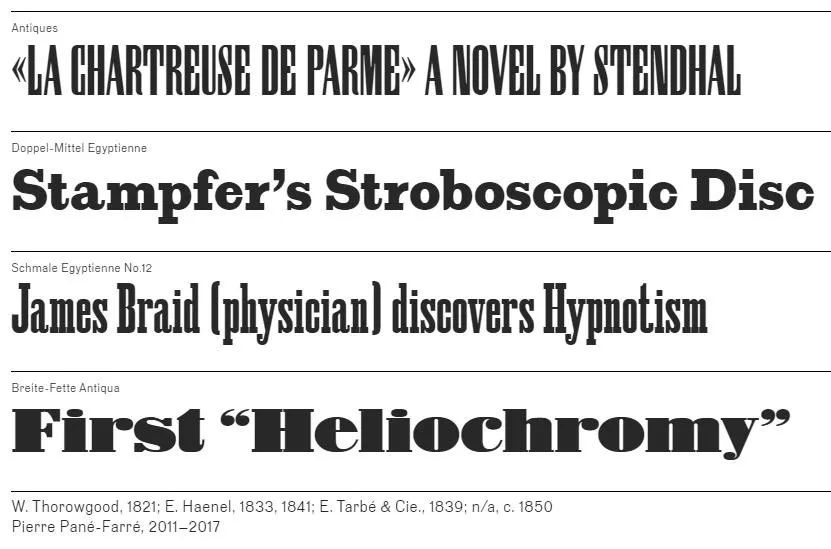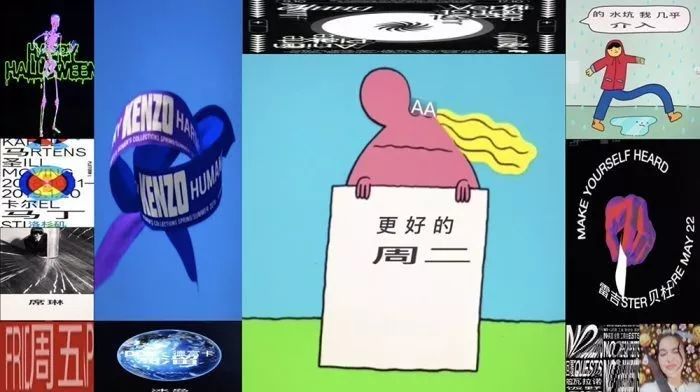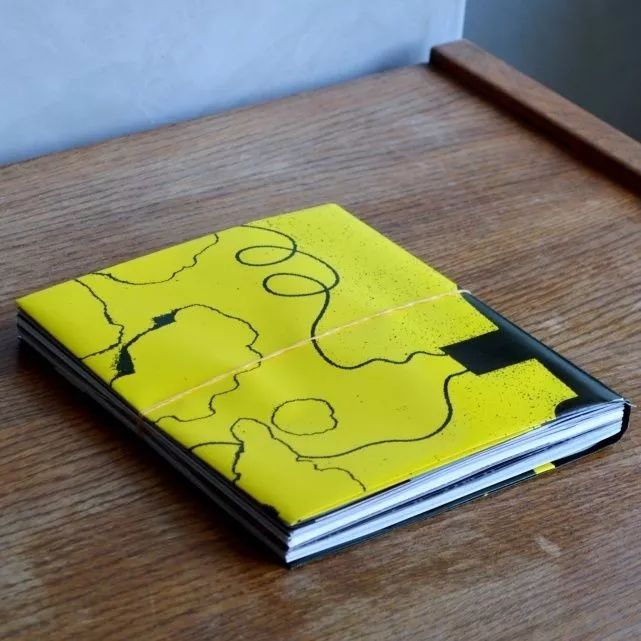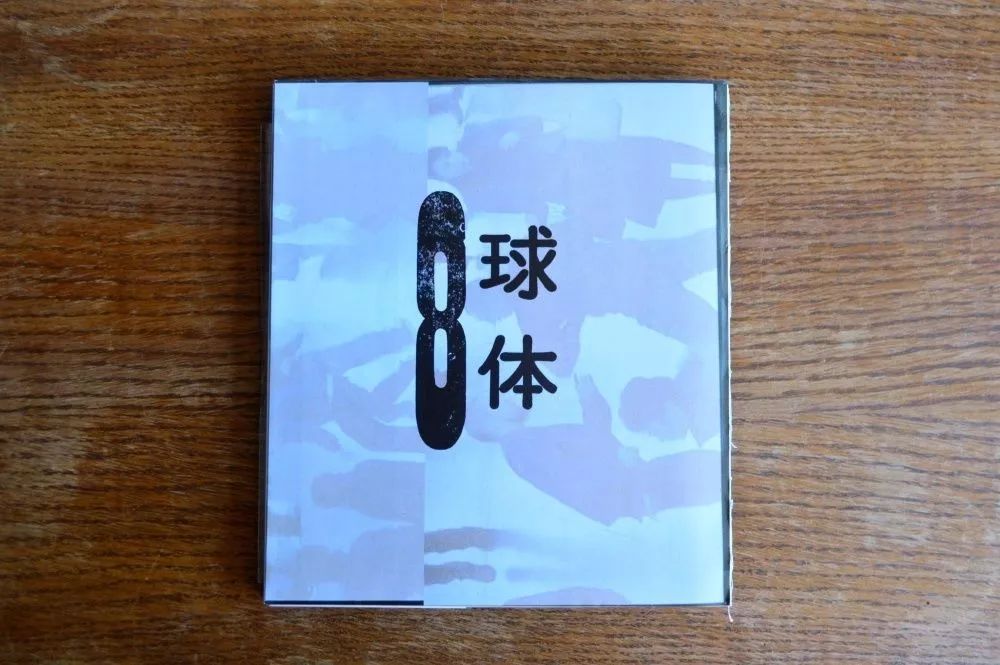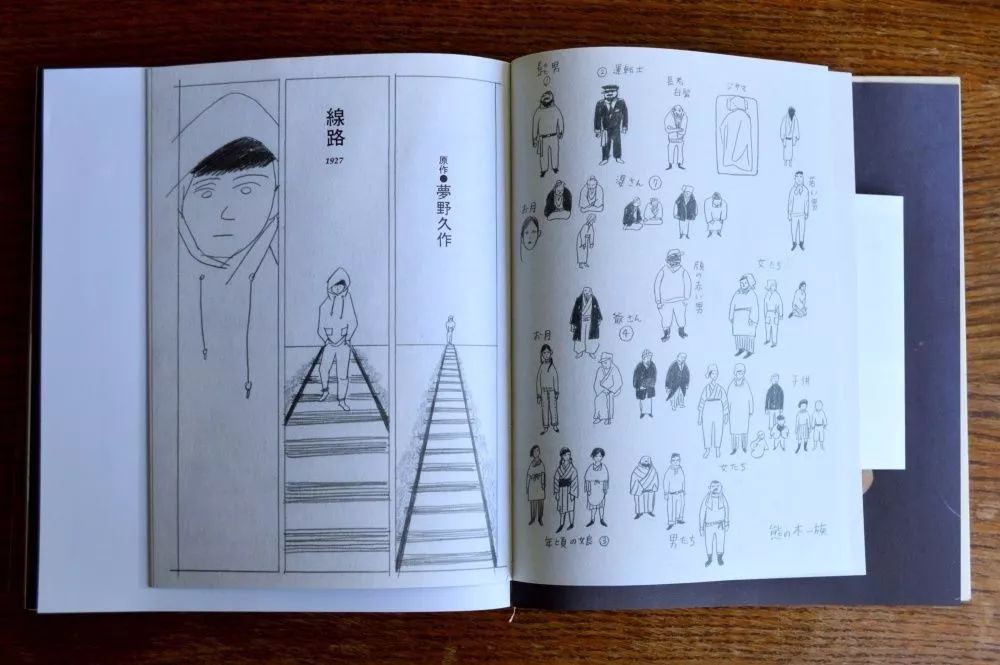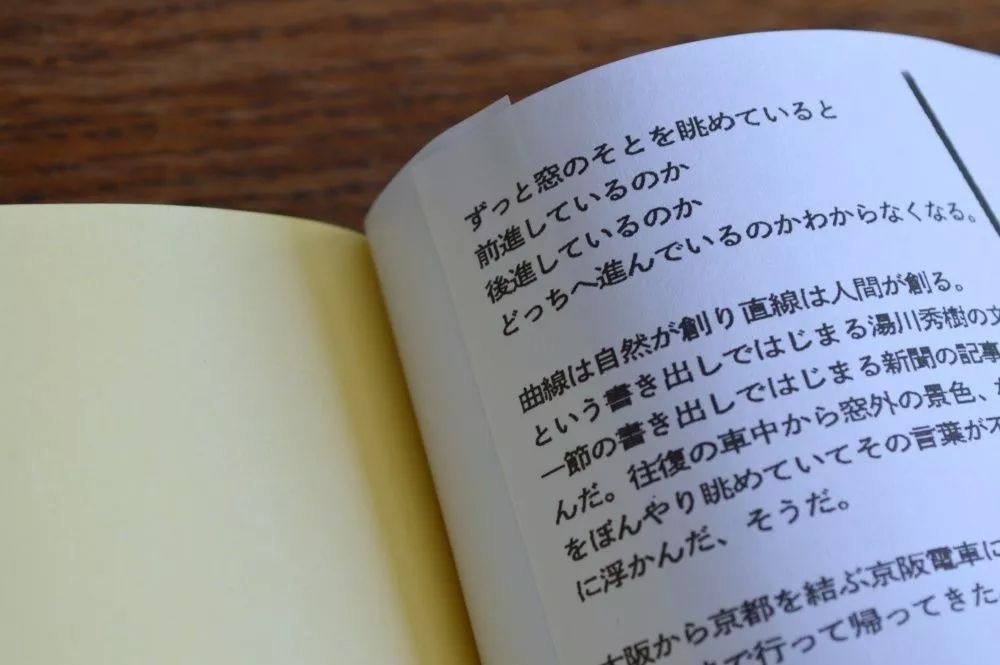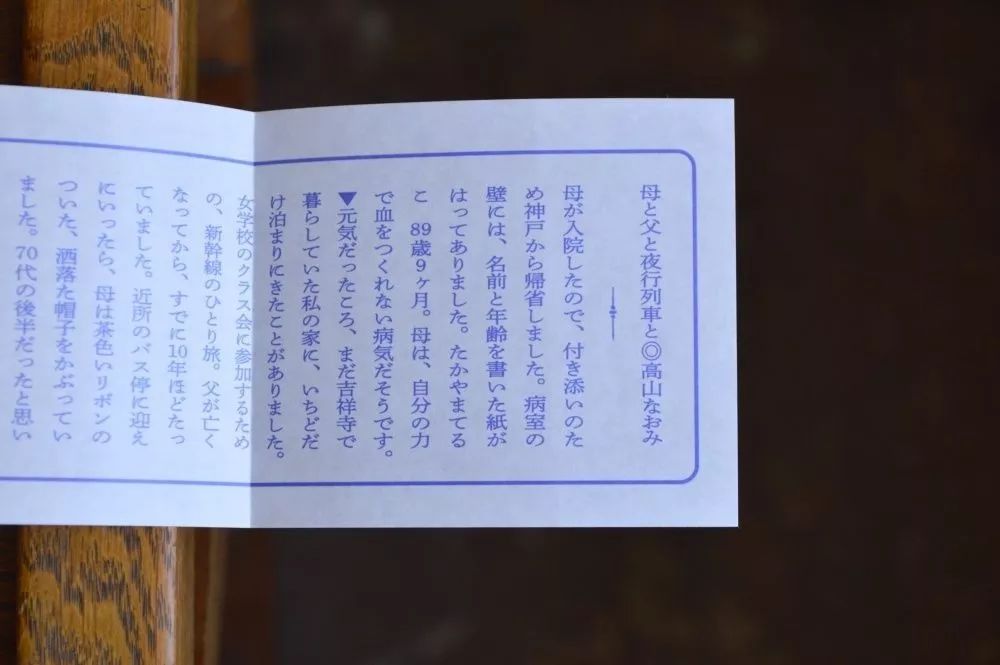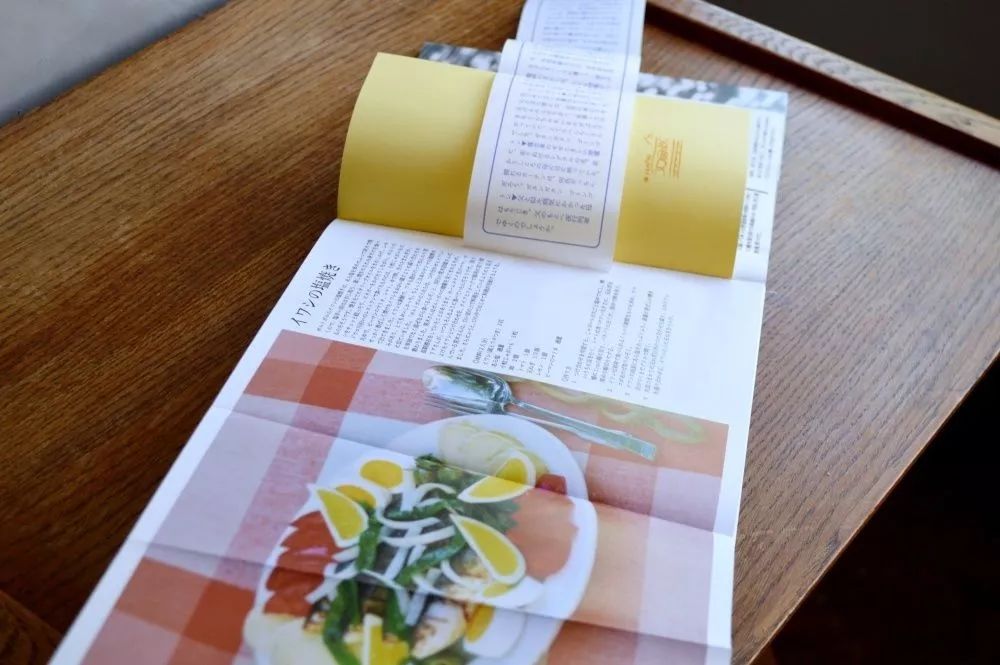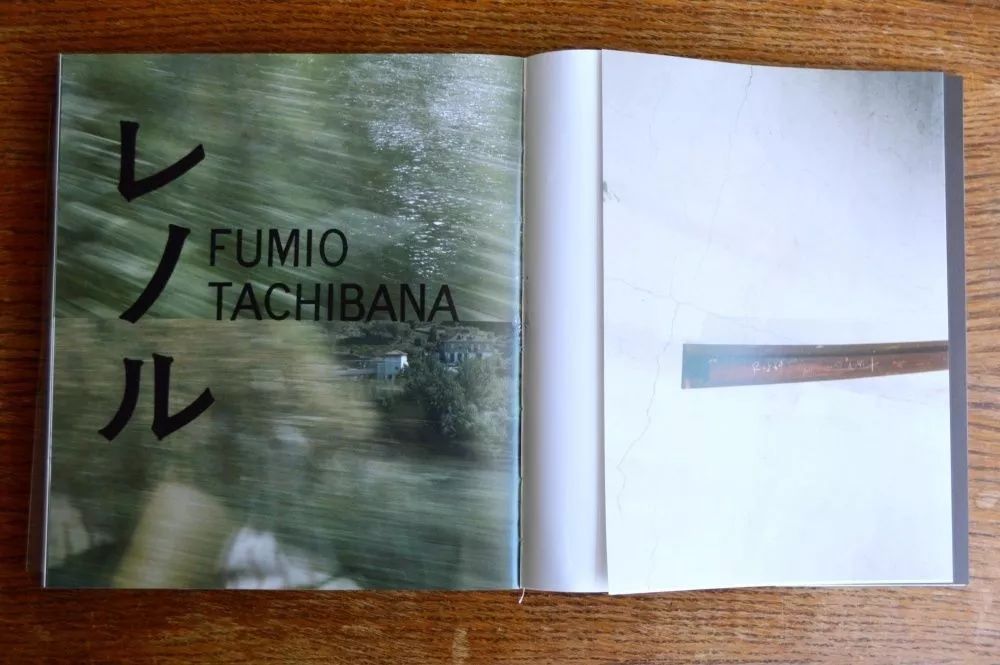
2020 Tokyo TDC获奖作品公布,2组中国设计师获奖
Tokyo TDC(东京字体指导俱乐部)成立于1987年,其宗旨是表现字体设计中文字和语言之间的深刻关联,同时也十分关注艺术指导者与企业诉求的关系,以及视觉艺术和平面设计的联通。它每年从世界各地收到优异的参赛作品,从中选拔出顶尖之作,并授予Tokyo TDC大奖。多年来,它不断挑战排版的定义与型式、字形和字体的平面设计,推动字体在印刷、广告、出版和屏幕的应用与创新,涉及当代字体设计各个领域,现在已经发展成为屈指可数的国际性设计年赛。
< Grand Prix >
Michael Amzalag + Mathias Augustyniak, M/M(Paris) [France]
Title: Galeries Lafayette Champs Élysées
Client: Galeries Lafayette Champs Élysées
Logotype, VI, Typeface
< RGB Prize >
Karen ann Donnachie + Andy Simionato [Australia]
Title: The Library of Nonhuman Books
Client: Atomic Activity Books
< Type Design Prize >
Pierre Pané-Farré [Germany]
Title: Affichen-Schriften FSL
Client: Forgotten Shapes
< Book Design Prize >
Jonathan Ellery + Lawrence Weiner [UK]
Title: HERE IT IS HERE IT AINT
Client: Browns Editions
< TDC Prize >
Akiem Helmling + Sami Kortemäki + Bas Jacobs, Underware [TheNetherlands]
Title: Grammatography
Client: Self initiated type technological development
Type Design Category
OK-RM (Oliver Knight + Rory McGrath) [UK]
Title: The Journey of Things: Magdalene Odundo
Client: InOtherWords / The Hepworth WakefieldType Design
Book Design Category
Panos Vassiliou + Manos Daskalakis [Greece]
Title: Marlet AntiManifesto
Client: Parachute Typefoundry
Small Graphics Category
梅数植 + 连杰 + 李习斌 [China](详细内容点击)
Title: Big, or Small
Client: MLX
RGB Category (Exhibition movie)
高田唯 Yui Takada [Japan]
Title: Yui Takada Exhibition Beijing| A Flower A Day
Client: NEUE DESIGN EXHIBITION PROJECT
Small Graphics Category (Exhibition graphics)
李习斌 + Liu Yutong [China]
Title: the benevolent enjoy mountains “仁者乐山”
Client: FounderType
Poster Category
< Special Prize >
井上嗣也 Tsuguya Inoue [Japan]
Title: COMME des GARÇONS SEIGEN ONO / CDG Fragmentation SEIGEN ONO
Client: NIPPON COLUMBIA CO., LTD.
Poster and Small Graphics Category (Poster + LP, CD jacket)
立花文穗  Fumio Tachibana [Japan]
Title: Kyutai 8 / STATION TO STATION
Client: Kyutai Editing
Book Design Category
*参赛作品总数:2783(日本参赛者为1529,海外参赛者为1254)
*除特等奖外,所有奖项的等级均相等。